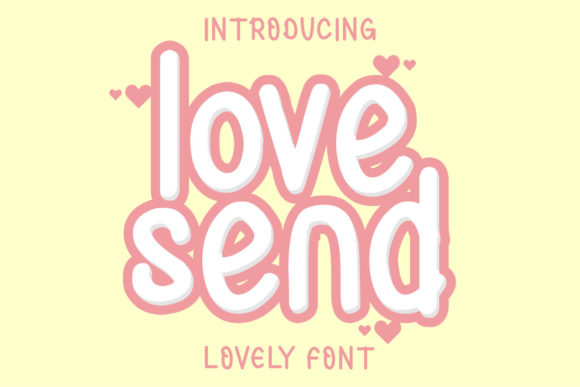
Название: Love Send Font (2021)
Love Send - это классный и аккуратный шрифт.
Этот шрифт подходит для дизайна футболок, спортивной одежды, логотипов, рекламы, одежды и многого другого.